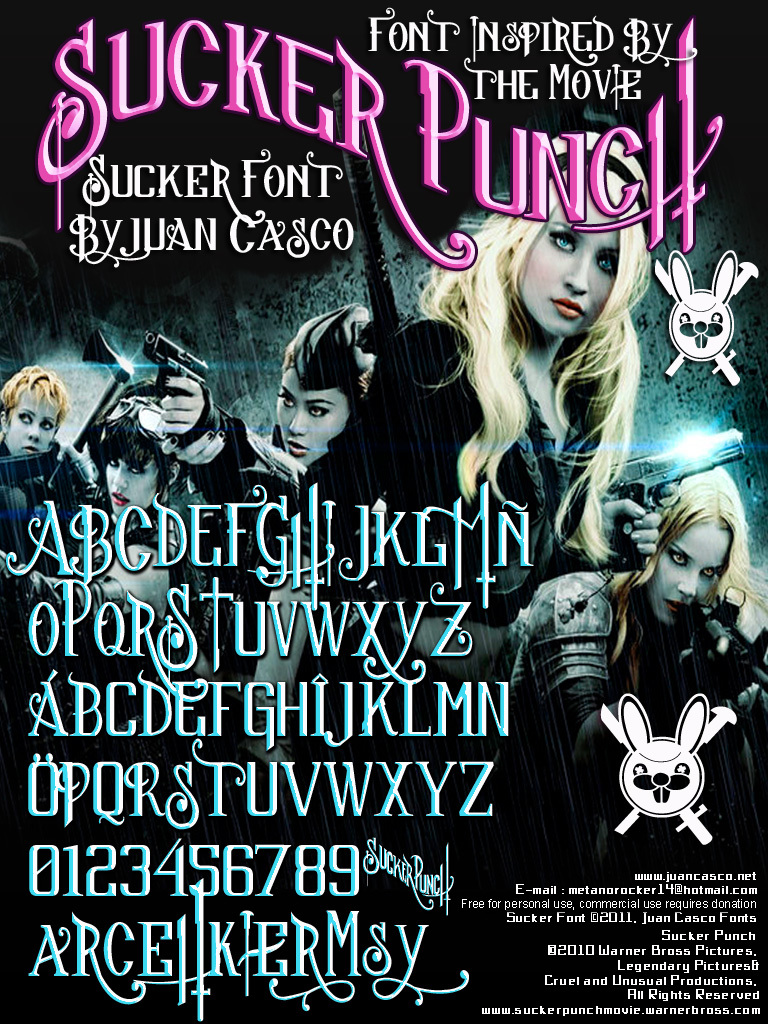
Sucker Font JC to urzekający krój typu display, który bez trudu przyciąga wzrok. Stworzony przez utalentowanego Juana Casco, ten członek rodziny Sucker Font emanuje unikalnym urokiem, łącząc fantazję z elegancją. Zdobne zawijasy i zabawne szeryfy przywołują estetykę vintage, co czyni go doskonałym wyborem do projektów, które mają się wyróżniać nutą stylu retro.
Płynność znaków Sucker Font JC sprawdza się w kreatywnych realizacjach wymagających artystycznego sznytu – od materiałów brandingowych i projektów logo po efektowne plakaty i nagłówki redakcyjne. Charakterystyczny styl tego fontu łączy tradycyjną finezję z nowoczesnymi trendami, zapewniając wszechstronność w różnych mediach.
Dzięki swojemu stylowemu wdziękowi, Sucker Font JC to nie tylko wybór typograficzny, ale wyrazista deklaracja – idealna propozycja dla projektantów, którzy chcą nadać swojej pracy osobowość i wizualną atrakcyjność.
Zainspirowano filmem "Sucker Punch".
Te greckie znaki są używane jako znaki alternatywne: